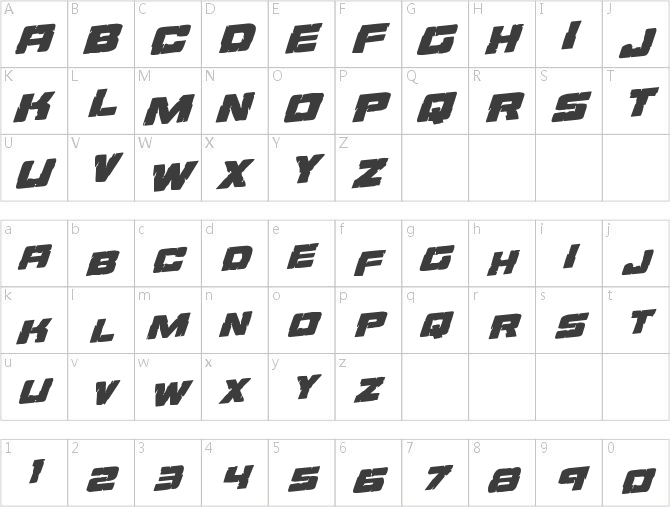
Ore-Crusher-Regular-Rotalic 詳情頁
Ore-Crusher-Regular-Rotalic字體字庫是一款讓人賞心悅目、百看不厭的英文字體,適合各類廣告和產(chǎn)品包裝設(shè)計應(yīng)用,字體大小0.08MB,格式為ttf字體,上傳用戶是我,Dirac,作者/版權(quán)方為未知